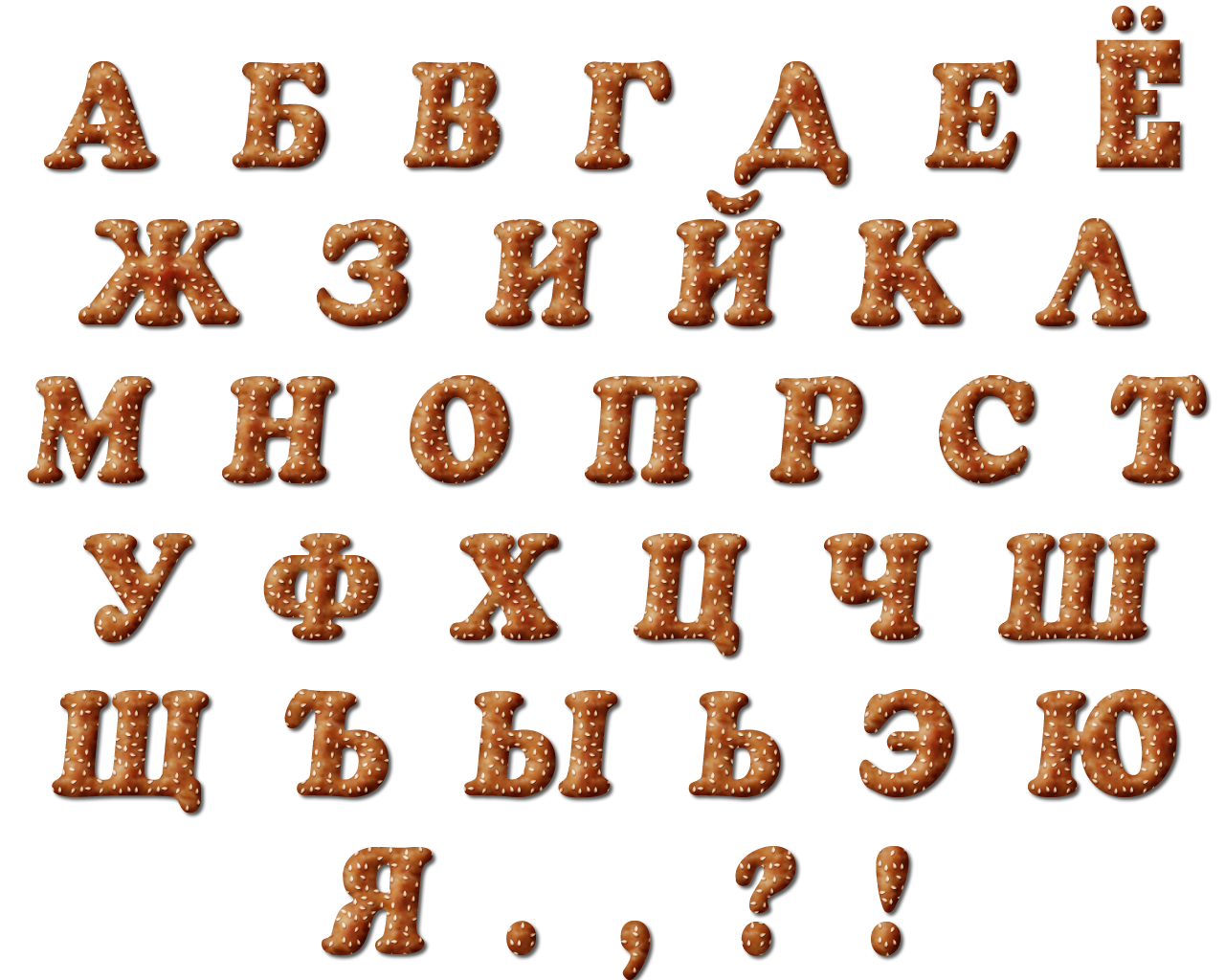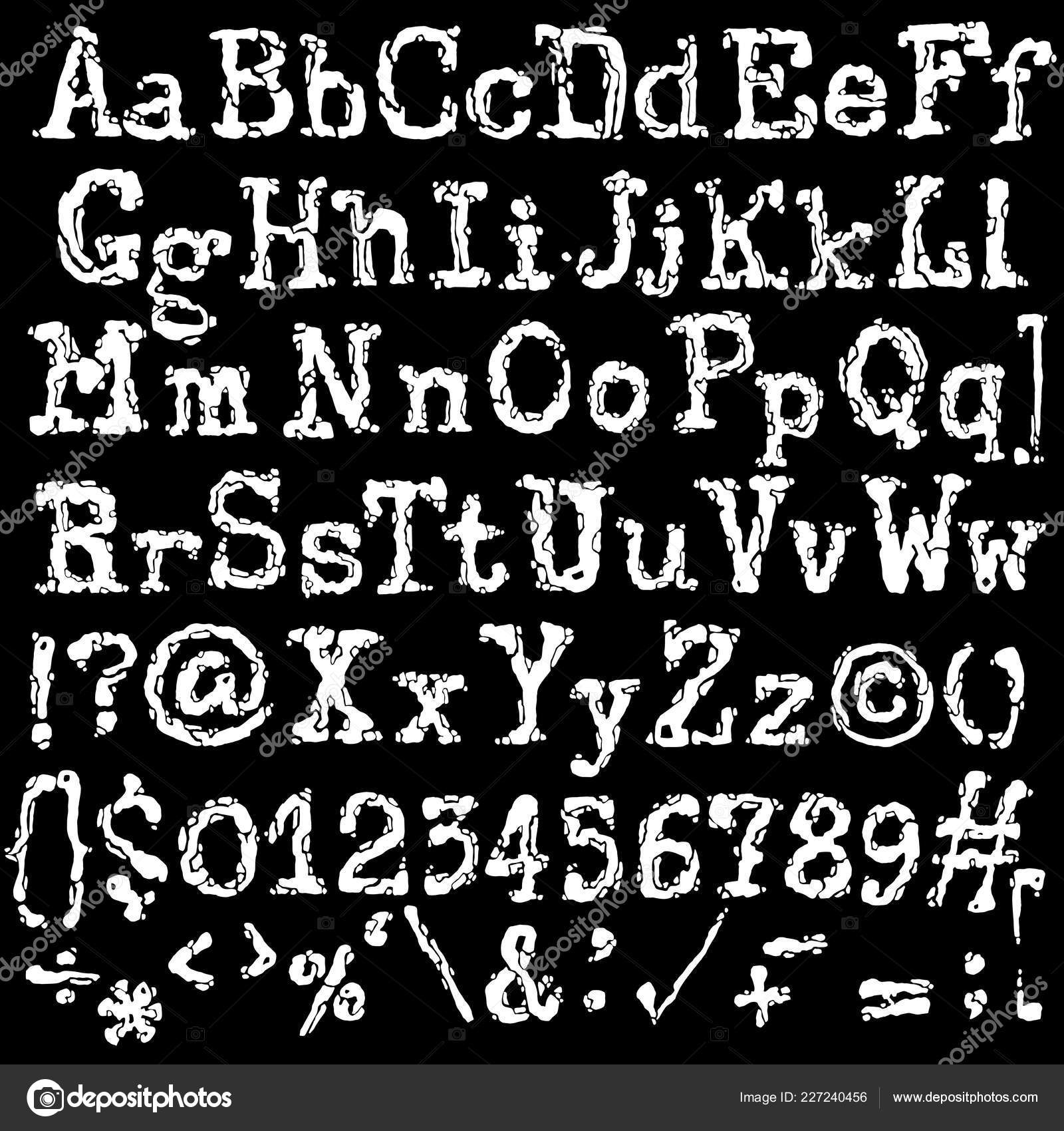
Шрифт старинный русский для фотошопа: Старинные русские шрифты
Каковы преимущества профессионально созданного веб-шрифта?
— поддержка языков и возможность настройки письма;
— несколько вариантов стилей и начертаний;
— подобранные кернинги.
Как правильно подобрать шрифт для интернет-проекта?
Главное требование, которое выдвигается к любому шрифту — это читаемость. Вы создаете сайты для людей, которые приходят на ваши страницы за информацией. Чтобы обеспечить им комфорт в потреблении контента, выбирайте только качественные наборы шрифтов. Русские шрифты скачать важно для аудитории, родной язык которой русский. Однако не стоит использовать на одном веб-проекте слишком много шрифтов, чтобы не путать и не рассеивать внимание читателей. Оптимальное количество используемых на сайте шрифтов — 2. К примеру, один из них можно использовать при создании заголовков, а другой — для публикации основного контента.
Так проекта будет выглядеть более привлекательным и целостным, а пользователи смогут легко отличать основной контент от второстепенного.
Шрифты бывают:
— с засечками (как правило, отличаются очень хорошей читабельностью, придают сайту элегантности и утонченности).
— без засечек (отличный вариант для сайтов в стиле минимализм).
— с прямоугольными засечками (если вам необходим стильный сайт, используйте этот тип шрифтов на его страницах).
— рукописные (придают индивидуальности и выглядят так, как будто текст написан от руки).
— прописные (шрифты могут использоваться в качестве декоративных вставок. Не рекомендуется выбирать их в качестве основного оформления для сайта).
— готические (еще один декоративный шрифт, который можно использовать, к примеру, на сайтах старинных вещей и магазинов антиквариата).
На самом деле, хороших шрифтов огромное количество. И еще больше вариантов их использования и совмещения. В качестве основного шрифта для сайта, к правило, выбирают стильные шрифты с засечками — так можно не сомневаться в читабельности проекта.
Afjat Trends Light
Элегантный и гуманный шрифт, который отлично подходит для любого проекта, шрифт Afjat Trends Light отличается высокой контрастностью и современным стилем, который отлично подходит для логотипов, приглашений, фраз, текста и многого другого.Как часть дизайна шрифта, Afjat также поддерживает кириллицу и другие языки.